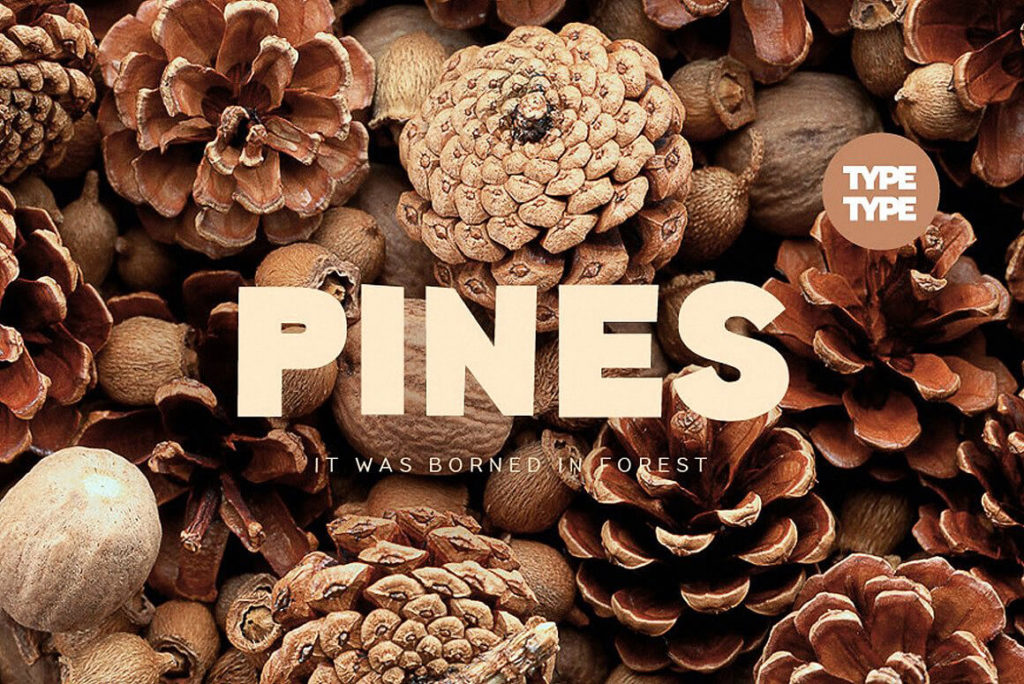
это дружелюбная семейство гротесков от студии TypeType, выпущенное в 2016 году. Его дизайн вдохновлен природными формами и ручной работой с деревом, что придает буквам теплоту и естественность. Это гуманистический гротеск с характерным рисунком, который отлично читается как в заголовках, так и в длинных кириллических текстах. Шрифт идеально подходит для эко-дизайна, упаковки натуральных продуктов и веб-интерфейсов, где нужен мягкий, но современный образ. Вы можете **скачать бесплатно** кириллические начертания TT Pines прямо сейчас, чтобы начать использовать их в своих проектах